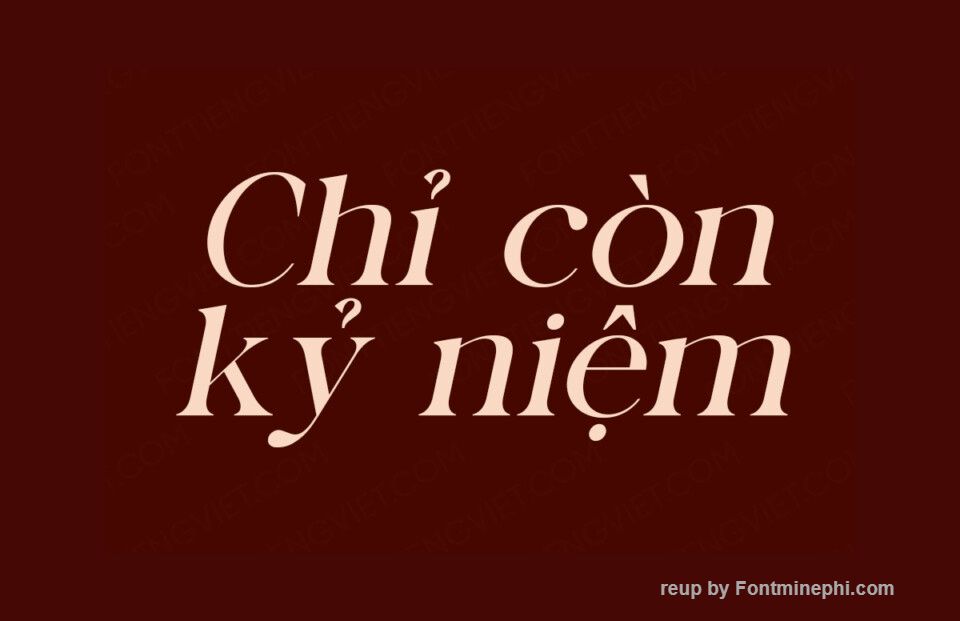
Font Việt hóa 1FTV VIP Ragille Italic là một trong những bộ phông chữ serif nghiêng cao cấp mang phong cách hiện đại, quyến rũ và đầy tính nghệ thuật. Được chế tác tỉ mỉ với các đường nét thanh đậm uyển chuyển, bộ font này giúp nâng tầm mọi dự án thiết kế từ nhận diện thương hiệu cá nhân đến sản phẩm truyền thông thương mại. Hãy cùng khám phá vẻ đẹp đẳng cấp và tính ứng dụng đa dạng của bộ font đặc biệt này ngay dưới đây.
Khám Phá Vẻ Đẹp Sang Trọng Của Font Việt Hóa 1FTV VIP Ragille Italic Trong Thiết Kế Đồ Họa
Thế giới thiết kế đồ họa luôn đòi hỏi sự đổi mới và tính sáng tạo không ngừng để tạo ra những sản phẩm truyền thông vừa thu hút thị giác, vừa truyền tải được tinh thần thương hiệu. Trong số các bộ phông chữ nghệ thuật hiện nay, font Việt hóa 1FTV VIP Ragille Italic nổi lên như một giải pháp thiết kế hoàn hảo nhờ vẻ đẹp tinh tế, kết hợp hài hòa giữa nét cổ điển quyến rũ và tinh thần hiện đại vượt thời gian.
Phiên bản Ragille Italic này được thiết kế đặc biệt nhằm phục vụ cho các ấn phẩm cao cấp như thiết kế thời trang, mỹ phẩm, thiệp cưới sang trọng, bìa tạp chí và logo thương hiệu. Với góc nghiêng chuẩn mực cùng các đường cong lượn mềm mại, 1FTV VIP Ragille Italic mang lại trải nghiệm thị giác sống động, giúp tác phẩm của bạn ngay lập tức ghi điểm mạnh mẽ trong mắt khách hàng và người xem.
1. Thiết Kế Serif Nghiêng Tinh Tế Với Nét Thanh Nét Đậm Sắc Sảo
Điểm nổi bật đầu tiên của font Việt hóa 1FTV VIP Ragille Italic chính là cấu trúc typography độc đáo. Sự kết hợp giữa phong cách serif chân phương cổ điển và góc nghiêng mềm mại của nét chữ Italic tạo nên một tổng thể cân đối, kiêu sa và giàu tính nghệ thuật.
Các đường nét thanh đậm được tinh chỉnh với tỷ lệ tương phản cao, tạo ra sự nhịp nhàng đặc biệt khi sắp xếp các dòng chữ. Nhờ vậy, từng ký tự khi đứng riêng lẻ hay kết hợp thành câu văn đều toát lên thần thái sang trọng. Đây là sự lựa chọn ưu tiên để làm nổi bật các tiêu đề lớn, slogan thương hiệu hay các đoạn trích dẫn cảm xúc trong các thiết kế đỉnh cao.
2. Việt Hóa Chuẩn Tỉ Mỉ Và Tối Ưu Hóa Typography Tiếng Việt
Một rào cản lớn đối với các nhà thiết kế Việt Nam khi sử dụng phông chữ nước ngoài là dấu tiếng Việt thường bị thô, lệch vị trí hoặc làm vỡ bố cục chung. Bộ font 1FTV VIP Ragille Italic đã được đội ngũ thiết kế Việt hóa lại một cách vô cùng chuyên nghiệp và kỹ lưỡng.
Hệ thống dấu tiếng Việt được vẽ lại hoàn toàn thủ công để đảm bảo sự đồng bộ tuyệt đối về nét vẽ, độ nghiêng và tỷ lệ với chữ gốc. Kỹ thuật điều chỉnh khoảng cách chữ (kerning) cũng được tối ưu hóa, giúp văn bản tiếng Việt hiển thị mượt mà, tự nhiên mà không xảy ra lỗi dính chữ hay đè dấu trên các phần mềm như Adobe Photoshop, Illustrator, InDesign, Canva hay Figma.
3. Bộ Glyphs Và Ký Tự Thay Thế (Alternates) Đa Dạng
Font Việt hóa 1FTV VIP Ragille Italic không chỉ dừng lại ở bộ ký tự chữ cái căn bản. Điểm đắt giá nhất của phiên bản VIP này chính là kho ký tự thay thế (Alternates), ký tự lượn (Swashes) và ký tự nối (Ligatures) cực kỳ phong phú được tích hợp sẵn qua tính năng OpenType.
Nhà thiết kế có thể dễ dàng biến tấu các chân chữ, thêm các đường uốn lượn mềm mại ở đầu hoặc cuối từ để tạo ra những kiểu chữ độc bản. Sự linh hoạt này giúp bạn kiến tạo nên những logo typographic đẳng cấp, các bản thiết kế bao bì thu hút mà không cần mất quá nhiều thời gian vẽ nét thủ công.
4. Khả Năng Ứng Dụng Đa Năng Cho Nhiều Lĩnh Vực Thiết Kế
Nhờ sở hữu phong cách sang trọng và hiện đại, font Việt hóa 1FTV VIP Ragille Italic có tính ứng dụng cực kỳ rộng rãi trong nhiều loại hình dự án khác nhau:
- Bộ nhận diện thương hiệu: Thiết kế logo, typography cho các thương hiệu thời trang cao cấp, viện thẩm mỹ, spa, sản phẩm chăm sóc da và trang sức.
- Ấn phẩm sự kiện & Thiệp cưới: Tạo điểm nhấn trang trọng, thanh lịch cho thiệp mời, menu tiệc, bảng đón khách trong các sự kiện cao cấp.
- Xuất bản & Tạp chí: Phù hợp làm phông chữ tiêu đề trang bìa, headline các bài viết về phong cách sống, nghệ thuật và kiến trúc.
- Bao bì sản phẩm: Thiết kế nhãn mác nước hoa, chai rượu vang, hộp quà tặng thượng hạng, góp phần nâng cao giá trị thương hiệu.
- Truyền thông Kỹ thuật số: Thiết kế banner quảng cáo, hình ảnh nhận diện mạng xã hội (Instagram, Facebook), giao diện website xa xỉ.
5. Tối Ưu Hóa Kỹ Thuật Và Hiển Thị Sắc Nét Trên Mọi Nền Tảng
Đặc biệt, phông chữ được tinh chỉnh để hiển thị cực kỳ sắc nét trên các màn hình độ phân giải cao (Retina/High-DPI), giúp từng nét thanh mảnh vẫn giữ nguyên độ chi tiết mà không bị mờ hay vỡ hạt.
Gợi Ý Kết Hợp Font 1FTV VIP Ragille Italic Đạt Hiệu Quả Thị Giác Tối Đa
Để khai thác hết vẻ đẹp của font Việt hóa 1FTV VIP Ragille Italic, việc phối hợp font chữ (Font Pairing) đúng nguyên tắc là vô cùng quan trọng. Dưới đây là một số bí quyết giúp ấn phẩm của bạn trở nên ấn tượng hơn:
- Kết hợp với Sans-serif tối giản: Sử dụng Ragille Italic cho các tiêu đề chính (Headline) và kết hợp với một font Sans-serif hiện đại, gọn gàng (như Montserrat, Helvetica, Futura) cho phần văn bản nội dung. Sự đối lập giữa nét uốn lượn nghệ thuật và nét thẳng hiện đại sẽ tạo ra sự cân bằng thị giác tuyệt vời.
- Tạo tương phản về kích thước: Tận dụng kích thước chữ thật lớn cho 1FTV VIP Ragille Italic để biến câu chữ thành trung tâm thu hút thị giác, kết hợp cùng các dòng chữ phụ có kích thước nhỏ và khoảng cách ký tự (tracking) mở rộng.
- Giữ khoảng trống hợp lý (White Space): Vì Ragille Italic chứa nhiều chi tiết uốn lượn quyến rũ, bạn nên dành nhiều khoảng không gian thoáng xung quanh để tôn lên vẻ đẹp tự nhiên của chữ mà không gây cảm giác chật chội.
Font Việt hóa 1FTV VIP Ragille Italic không chỉ đơn thuần là một phông chữ gõ văn bản, mà là công cụ sáng tạo đỉnh cao giúp nâng tầm giá trị cho mọi dự án thiết kế. Với sự kết hợp tinh tế giữa nét serif nghiêng thanh lịch, chuẩn mực tiếng Việt hoàn hảo và hệ thống ký tự thay thế đa dạng, bộ font này chắc chắn là vũ khí đắc lực không thể thiếu của các nhà thiết kế chuyên nghiệp.